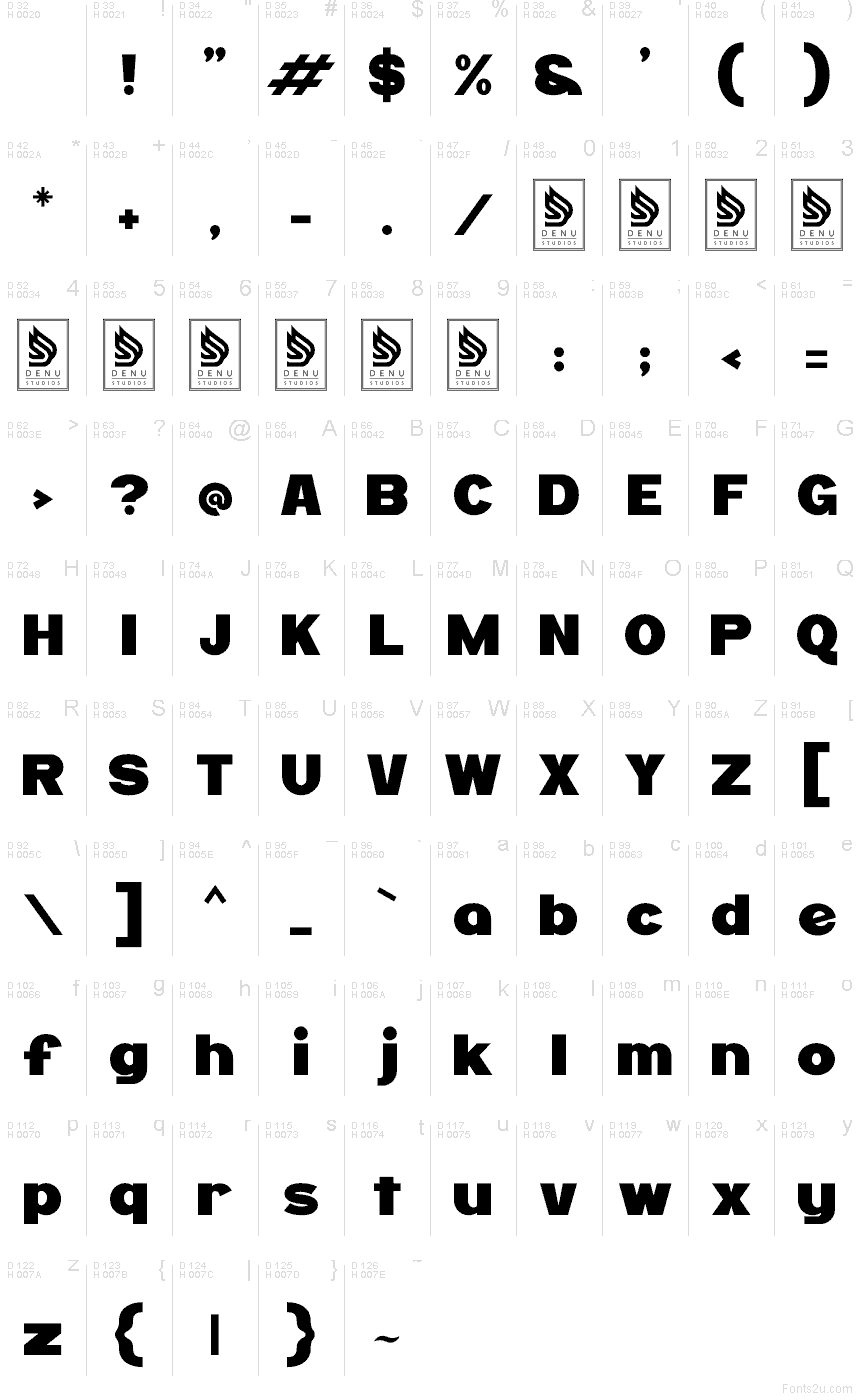
Nolang, da Denustudios, é uma tipografia sem serifa geométrica gratuita com uma presença marcante, perfeita para pôsteres. As letras parecem construídas a partir de formas largas e arredondadas e cortes retos, conferindo à fonte um ritmo compacto que soa mais contemporâneo do que neutro.
Ela encaixa-se naturalmente em branding, arte de capas de música, gráficos de streetwear, ecrãs de início de aplicações e títulos editoriais onde é necessário peso visual. Sendo uma fonte gratuita, também é ideal para títulos e nomes curtos em embalagens, especialmente quando deseja formas circulares suaves para equilibrar o bloco maciço das letras.